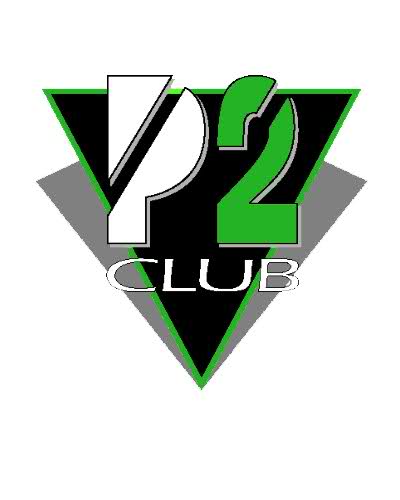
Schriftart gesucht nach Bildvorlage, nehme an aus den 80ern
Ich habe eine Frage an euch Spezialisten hier betreffend einer Schriftart aus folgendem Bild:
Es geht hauptsächlich um die Zeichen "P" und "2".
Weiss jemand von euch welche Schriftart diese sein könnte oder zumindest welche dieser hier sehr nahe kommt?
Und wenn einem zufällig noch die Schriftart von "CLUB" auffällt welche das sein könnte dann wäre das auch sehr hilfreich für mich.
Ich hab schon tausende Schriftarten durchsucht aber ich weiss nicht mal unter welcher Kategorie ich nachschauen soll...
P2 ist bestimmt etwas gebasteltes, keine Schriftart. Da stimmen ja die internen Proportionen schon gar nicht.
CLUB könnte eine vom Trecker überfahrene Eras sein.
Wenn man den Gestalter so behandeln würde, wie der die Schrift behandelt hat, würde man wahrscheinlich eine mehrjährige Haftstrafe bekommen.
Hehe, das ist gut. Club kann gut hinkommen.
Für P2 würde Dir auch nichts ähnliches einfallen?
Na ja, wenn Du eine Futura extra bold condensed als Basis nimmst und ihr mit Kettensäge und Vorschlaghammer zu Leibe rückst, hast Du das in fünf Minuten gebastelt. Ist halt nur schade drum.
Sei froh, daß Du diese deformierte „Schrift“ nirgendwo gefunden hast.
Entfernt ähnlich sind Schablonenschriften, bei denen ja ebenfalls Buchstabenteile ausgespart sind. Diese findest Du unter dem Stichwort „Stencil“ zum Beispiel bei myfonts, oder auch in kostenlosen Schriftarchiven, etwa auf dafont oder hier.
Ansonsten kann man sowas ja auch leicht aus einer normalen Schrift ableiten.
Hast Du vor, das Logo neu zu erstellen? In diesem Fall rate ich dringend, es zu überarbeiten.
Nein, das Logo wird nicht neu erstellt, aber ich möchte etwas mit dem Logo gravieren lassen und als Zusatz einen Namen drauf in gesuchter Schrift.
Ich bin leider nicht so bewandert dass ich mir selber eine Schriftart erstellen kann.